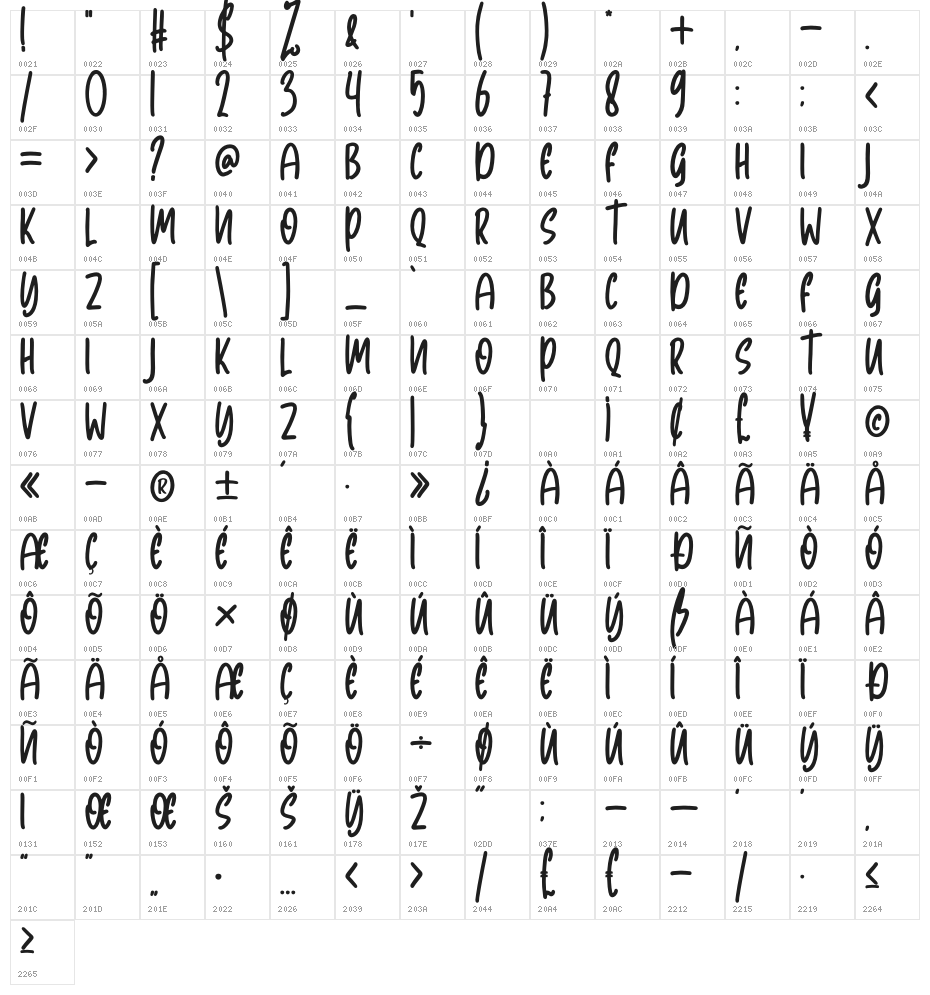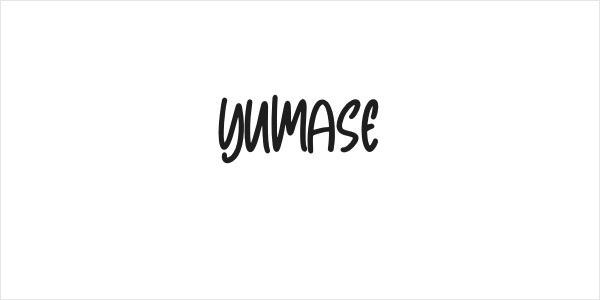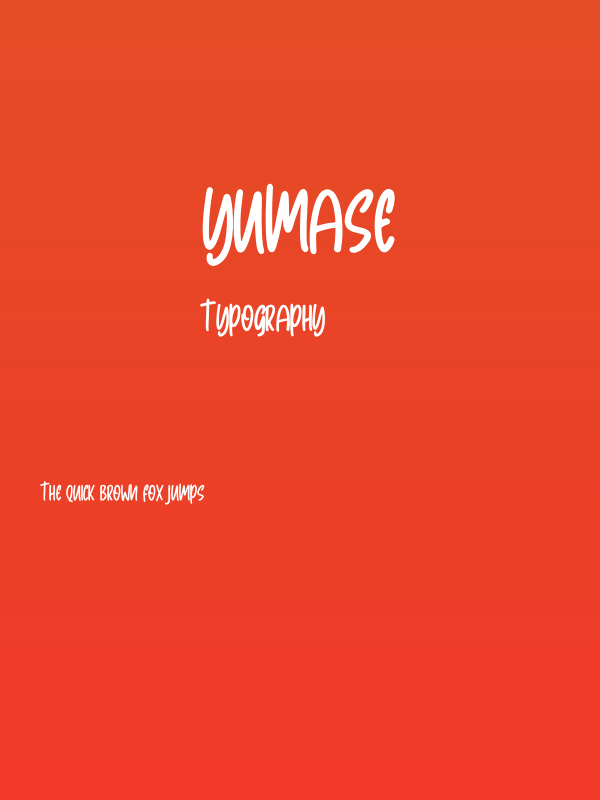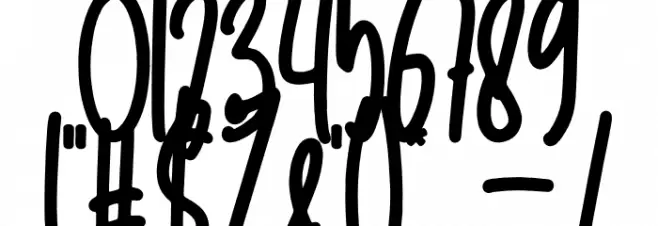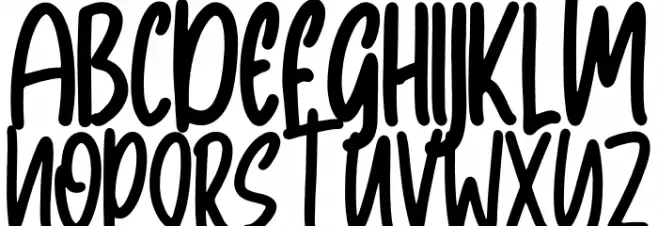
Yumase Font
YUMASE أحرف كبيرة
YUMASE أحرف صغيرة
YUMASE محارف أخرى
| الاسم | Yumase |
| عائلة الخط | Yumase |
| العرض | Condensed |
| النمط العام | Modern, Playful |
| حالة الاستخدام | Headlines, Logos, Creative projects |
| مشاريع مقترحة | Ideal for greeting cards, posters, social media graphics, and branding projects that require a personal touch. |